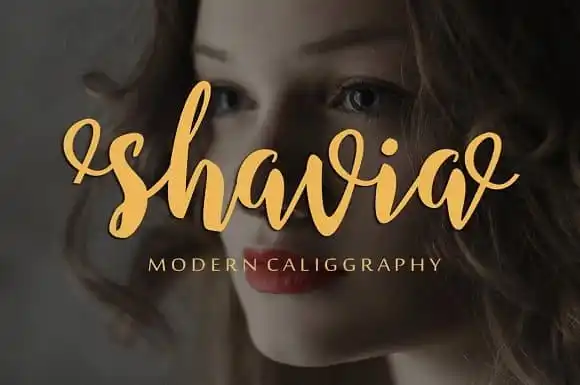
Shavia Script Font – Download Grátis
A Shavia é uma fonte calligrafia moderna que oferece um toque orgânico e dinâmico, criando um estilo vibrante e vital. Esse design fluido é perfeito para diversas aplicações, incluindo casamentos, logotipos, cartões de convite, marca identidade, anúncios impressos, citações, sinalização e publicações em geral. Com seu charme único, a Shavia se destaca como uma escolha ideal para quem busca um toque especial em seus projetos. Suas linhas curvas e seu formato levemente ondulado adicionam um toque de elegância e modernidade, tornando-a perfeita tanto para trabalhos formais quanto para produções mais criativas. Através da Shavia, você pode dar vida a qualquer projeto gráfico, adicionando personalidade e sofisticação. Seja em cartões de casamento com um toque de delicadeza ou em uma identidade visual que transmite vitalidade e atrevimento, essa fonte é o elemento ideal para destacar seu design. Incorporar a Shavia em seus projetos vai além do simples uso de letras; ela é uma maneira de expressar sua identidade gráfica de forma única, criando um design singular que se destaca nas mídias onde ela for aplicada.